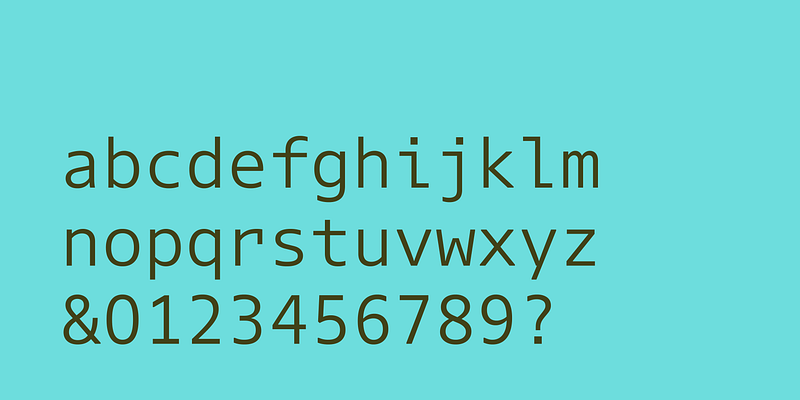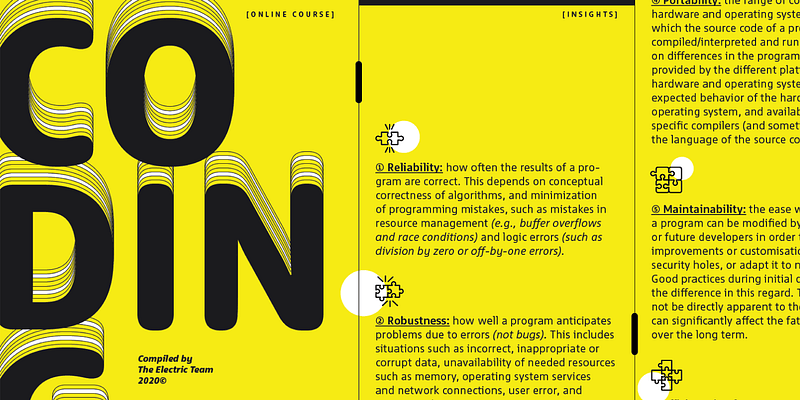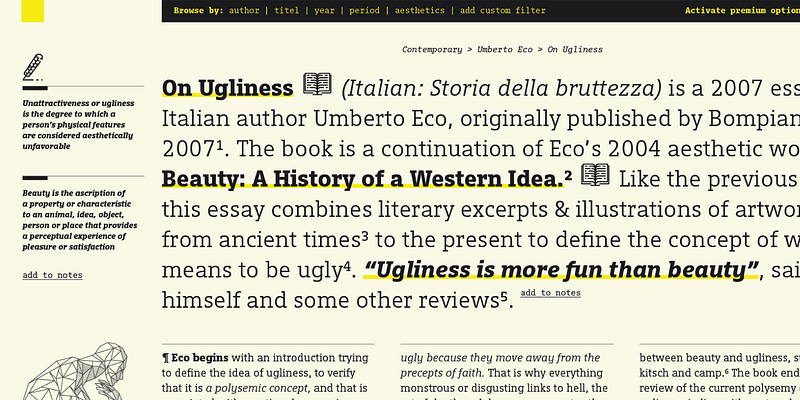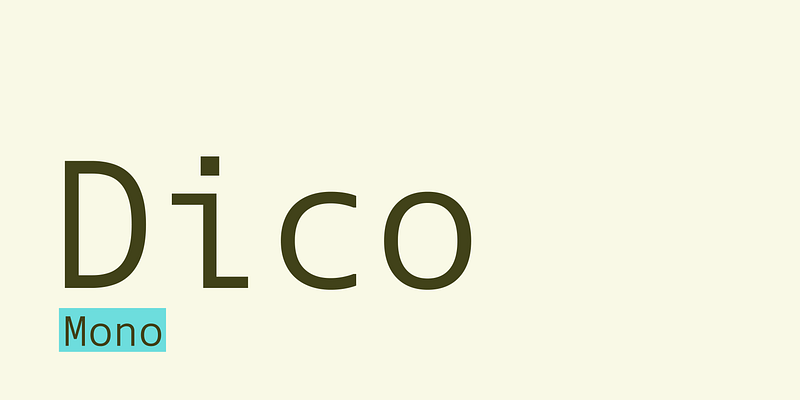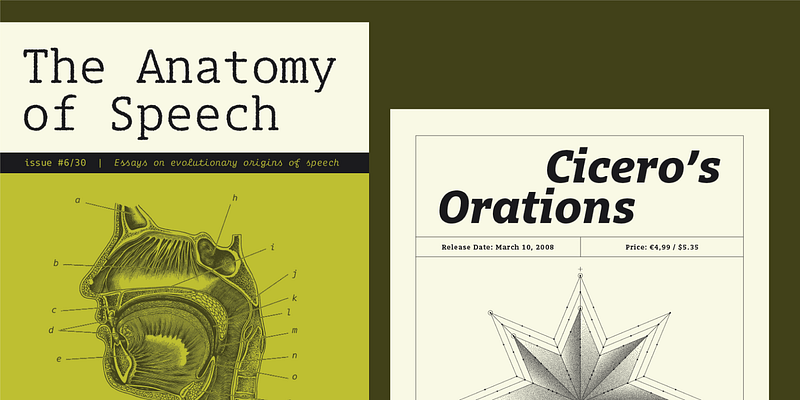
La structure et le comportement de base de Dico (en latin, « je dis, je parle, je prononce un discours ») sont façonnés par des proportions compactes et des formes de lettres ouvertes mais sobres qui gagnent en convivialité et en douceur lorsqu’elles sont accompagnées de leurs italiques plus audacieuses. Les styles de polices à espacement fixe (vaguement inspirés de Corinthian Script pour IBM Selectric) peuvent donner une tournure encore plus originale au texte. La gamme de graisses peut sembler étroite par rapport à d’autres grandes familles de polices, mais Dico compense largement cet inconvénient avec d’autres variations de thème correspondantes. Outre la variante Sans, vous avez le choix entre Slab Serif, Dico Soft arrondi, Sans serif et Slab à espacement fixe, deux variantes de Code et Dico Typewriter contenant des versions « brutes » de Dico Mono Sans, Mono Slab et Mono Script. 45 polices au total.